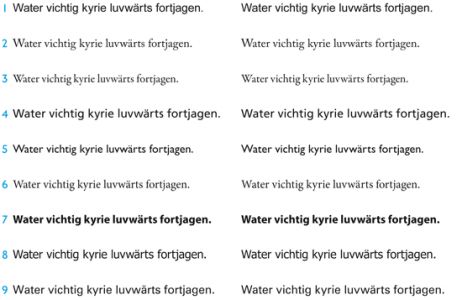
Optische vs. Metrische Zurichtung in InDesign
Ich habe mir die Sache mit der Einstellung »Optisch/Metrisch« im Kerning in InDesign noch einmal schnell zu Gemüte geführt. Ich habe mir eine Seite mit 9 unterschiedlichen, verbreiteten Schriften gebastelt und jeweils mit »Optisch« | »Metrisch« gegenüber gestellt.
Anschließend habe ich einen Ausdruck gemacht und jeweils einen Sieger gekürt. Das Ergebnis war nicht eindeutig. Einmal empfand ich die metrische Version besser, einmal die optische.
Ich muss zugestehen:
1. Ich bin höchstens »Hobby-Schriftdesigner«, also kein absoluter Profi im Zurichten von Schriften.
2. Mein 600dpi-Drucker ist absolut nicht erste Wahl für so einen Test.
Als Versuchsanordnung würde ich problematische Buchstabenkombinationen sehr groß anlegen, z.B. mit 48pt. um die Räume zwischen den Buchstaben zu sehen bzw. ob das jeweilige Kerning damit zurecht kommt. Und dann metrisch wie optisch vergleichen.
Bei dir sind die Schriftgrößen zu klein angelegt, zumindest für mich und mein noch nicht so geübtes Auge. Mit der Acrobat-Lupe kann ich zwar "unendlich" vergrößern, aber das hat ja dann nichts mit dem jeweiligen Kerning der Schrift zu tun (oder?).
Aber egal was du einstellst (m oder o), händisch anpassen muß man ja sowieso bei Displaygrößen ...